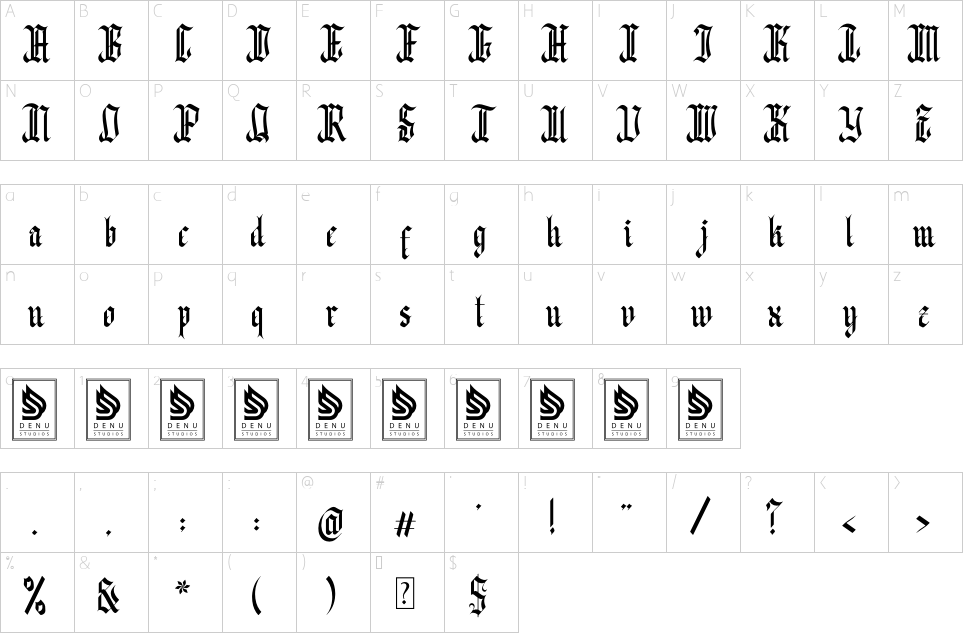
A Pelysska Font, criada pela Denustudios, é uma opção de fonte elegante e fluida que se adapta perfeitamente para vários tipos de projetos. Seja para o design gráfico, publicidade ou até mesmo para a criação de sites pessoais, essa fonte proporciona um visual único e sofisticado. Com seu design cuidadosamente elaborado, a Pelysska atinge um equilíbrio perfeito entre estética e funcionalidade. Ela foi popular entre os usuários, com 546 downloads, evidenciando seu valor e qualidade. Descubra por si mesmo, ou incentive sua equipe a experimentar a Pelysska Font e enriqueça seus projetos com seu charme inconfundível.